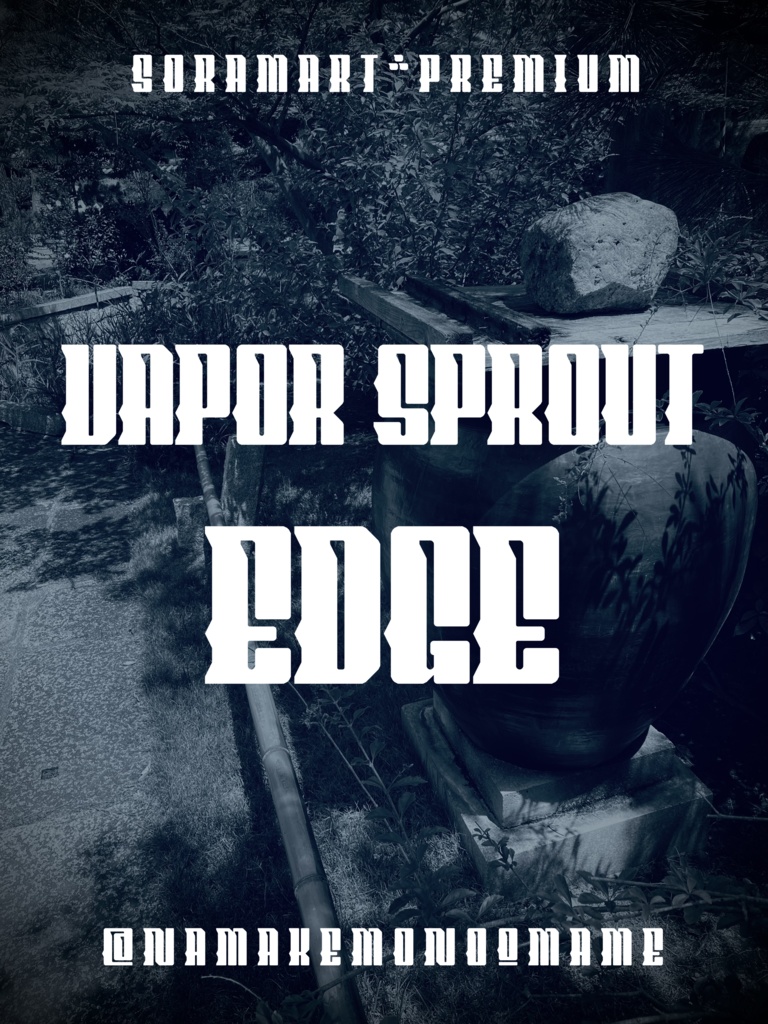
そらマートフォントデータ”Vapor Sprout Edge”Digital2,500 JPY카트에 담기기프트 보내기About Giftレトロモダン調の超縦長フォントにトゲトゲの装飾を加えた "Vapor Sprout Edge" です。 「TrueTypeフォントファイル」という形式です。 ダウンロードした後、Zipファイル内のデータをインストールしてお使いください。 このフォントは商用利用可となっております。 お客様の制作・創作活動のお役に立てれば幸いです。 ※使用上の注意事項などは、添付のReadmeをお読みください。 ※このフォントは、有料販売専用商品です。そらマートVisit FANBOX!Fontsフォントデータ”Solid Voltage Strike”そらマート200 JPYFontsフォントデータ”Solid Voltage”そらマート0 JPYFontsフォントデータ”Henge Edge Rock”そらマート2,500 JPYFontsフォントデータ”Henge Edge Tall”そらマート0 JPYFontsフォントデータ”Henge Edge”そらマート0 JPYFontsフォントデータ”Chisel Stroke Wide”そらマート2,500 JPYFontsフォントデータ”Chisel Stroke”そらマート2,500 JPYFontsフォントデータ”Crushed Can Serif Empty”そらマート2,500 JPYFontsフォントデータ”Crushed Can Serif Wide”そらマート2,500 JPYFontsフォントデータ”Crushed Can Serif”そらマート2,500 JPYFontsフォントデータ”Dolce Cube Tall”そらマート2,500 JPYFontsフォントデータ”Dolce Cube”そらマート2,500 JPYFontsフォントデータ”Eight-bit Quest Wide”そらマート2,500 JPYFontsフォントデータ”Eight-bit Quest”そらマート2,500 JPYFontsフォントデータ”Tonik Crate”そらマート2,500 JPYFontsフォントデータ”Vapor Sprout Wide”そらマート2,500 JPYFontsフォントデータ”Vapor Sprout”そらマート2,500 JPYFontsフォントデータ”Star Shoot Ray”そらマート2,500 JPYFontsフォントデータ”Star Shoot Black Wide”そらマート2,500 JPYFontsフォントデータ”Star Shoot Black”そらマート2,500 JPY더보기